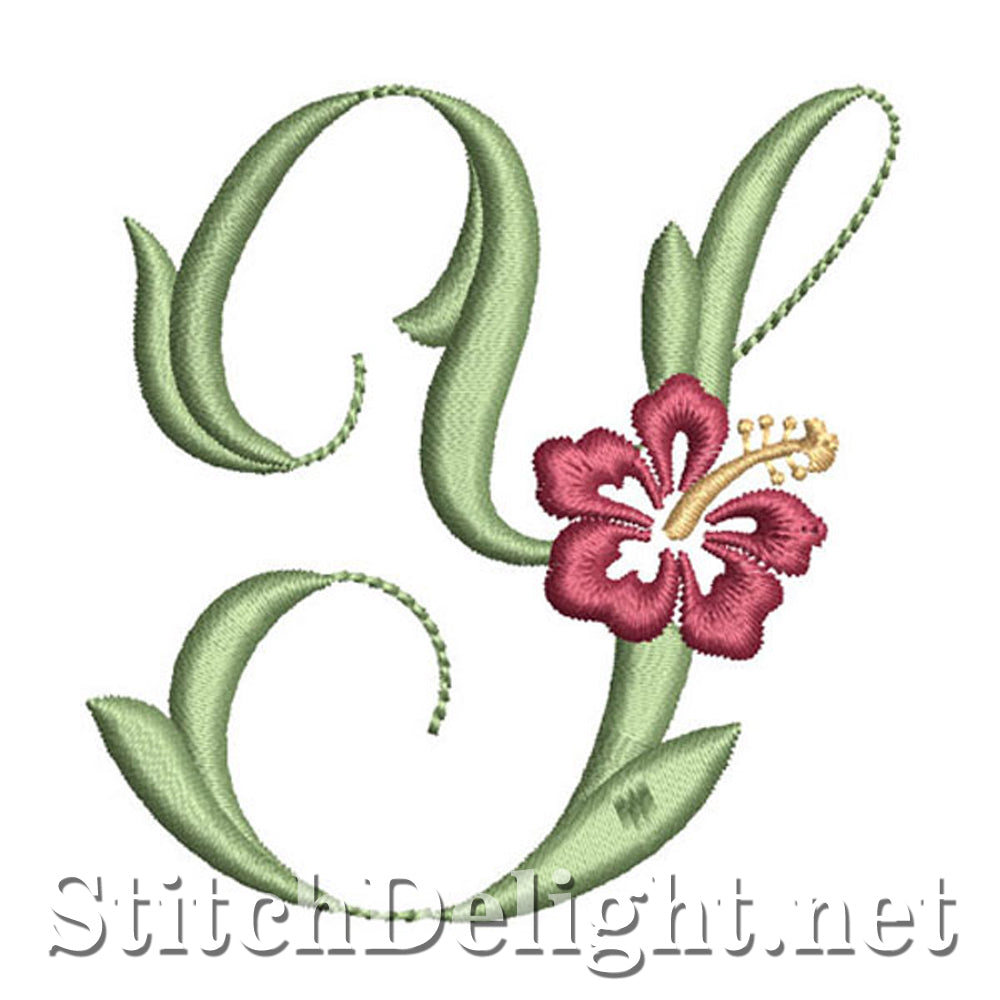
SDS1143 Hibiscus Schriftart Y
Schöne ausgefallene Buchstaben mit einer wunderschönen Hibiskusblüte - Die Buchstabenhöhe dieser Buchstaben beträgt 2,60"